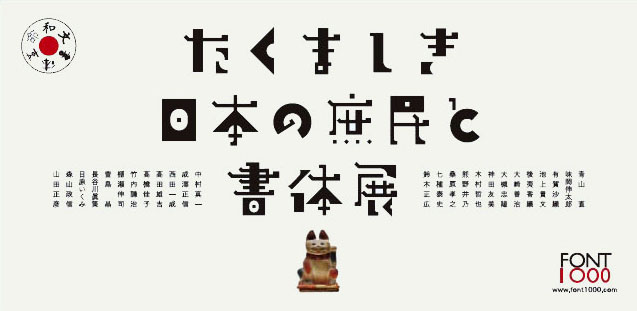
日本語書体開発の壁となる膨大な文字数。「すべての書体にこれほど多くの文字数が必要なのだろうか」という疑問のもと、「書体をつくってみたい」という多くのグラフィックデザイナーが気軽に手をあげられる環境はできないものか-。そんな思いからスタートしたFONT1000。2001年、参加デザイナー25名/25書体からはじまったその活動は、現在参加デザイナー36名/132書体と大きなものとなった。「和文書体革命」という理念を掲げ、この10年間で発表してきたわれらのたくましい書体の姿を、ぜひご覧いただきたい。